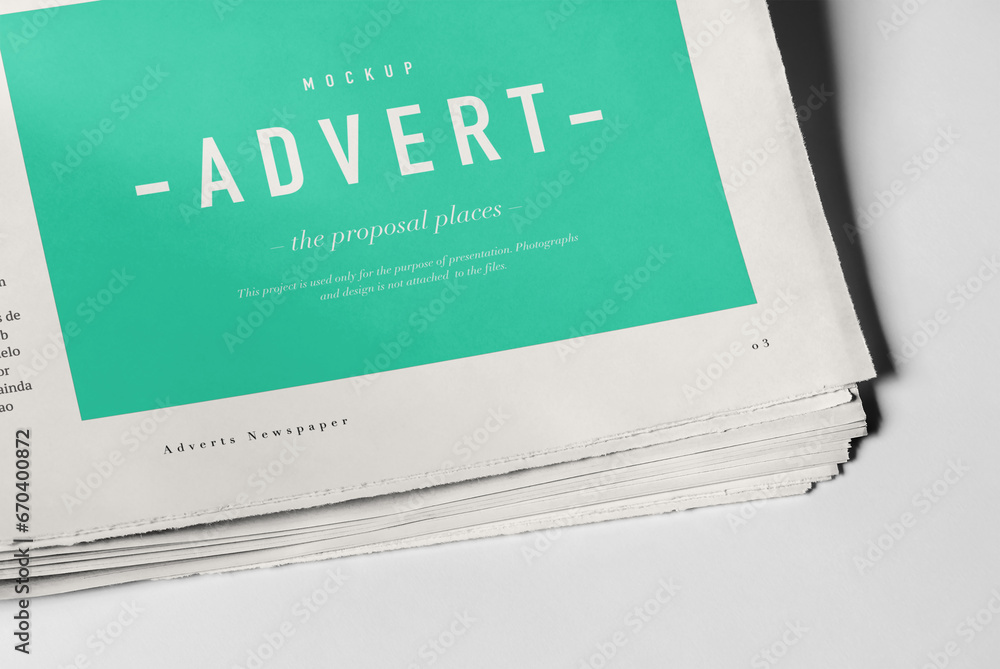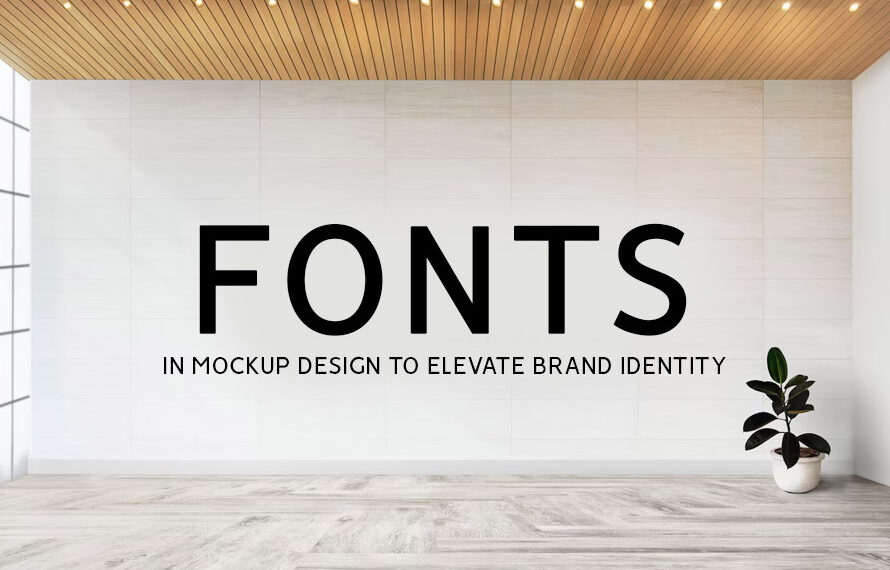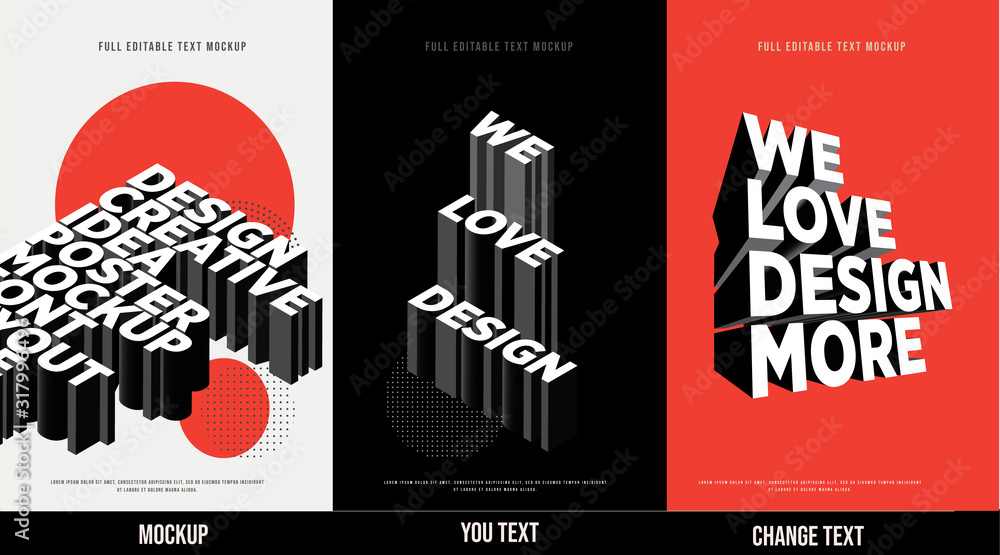
Fonts In Mockup Design
Nutzung von Schriftarten im Mockup-Design zur Steigerung der Markenidentität
Stellen Sie sich vor, Sie gehen eine belebte Straße entlang: Eine Flut von Geschäften zieht vorbei, die alle um Ihre Aufmerksamkeit konkurrieren. Plötzlich fällt Ihnen ein einzelnes Fenster ins Auge. Die klaren Linien, die fette Schriftart, die einladende Farbpalette – all das spricht Sie an und lädt Sie näher ein. Das ist die Kraft einer gut gestalteten Markenidentität.
Wenn es um Design geht, sind Ihre Schriftarten nicht nur Buchstaben auf einer Seite. Sie sind die Stimme Ihrer Marke, die Persönlichkeit und Zweck Ihrem Publikum zuflüstern. Tatsächlich können Ihre Schriftarten, einmal strategisch in Ihre Mockups integriert, wahre Magie entfalten, um Ihre Markenidentität zu verbessern. Lesen Sie weiter, um mehr zu erfahren.
Schriftarten in Ihrem Mockup-Design
Auswahl der richtigen Schriftart
Um Schriftarten in Ihrem Mockup-Design effektiv zu nutzen, ist Ihr erster Schritt die Auswahl der richtigen Schriftart. Denken Sie darüber nach, welches Gefühl Sie mit Ihrer Marke hervorrufen möchten. Verspielt und energiegeladen? Eine verspielte Skript-Schriftart könnte passen. Sophistiziert und zeitlos? Eine klassische Serifenschrift könnte die Antwort sein. Berücksichtigen Sie, wie die Schriftart mit der Kernbotschaft übereinstimmt, die Sie vermitteln möchten.
Fühlen Sie sich von all den Auswahlmöglichkeiten überwältigt? Keine Sorge, hier sind einige Faktoren, die Sie bei der Auswahl der idealen Schriftart beachten sollten.
Markenpersönlichkeit
Ist Ihre Marke verspielt und energiegeladen? Eine verspielte Skript-Schriftart könnte passen. Streben Sie nach einem anspruchsvollen und zeitlosen Eindruck? Eine klassische Serifenschrift könnte die Antwort sein.
Zielgruppe
Wen versuchen Sie zu erreichen? Ihre Schriftarten-Auswahl fällt leichter, wenn Sie die demografischen Merkmale und Vorlieben Ihrer Zielgruppe kennen. Zum Beispiel könnte eine jüngere Zielgruppe gut auf eine trendige, moderne Schriftart reagieren. Im Gegensatz dazu könnte eine professionelle Zielgruppe sich besser mit einer traditionellen Schriftart identifizieren.
Lesbarkeit
Die schönste Schriftart der Welt nützt Ihnen nichts, wenn sie schwer zu lesen ist. Priorisieren Sie Schriftarten mit klaren Buchstabenformen und angemessenem Abstand sowohl für digitale als auch für gedruckte Anwendungen.
Wählen Sie nicht einfach eine hübsche Schriftart aus! Die von Ihnen gewählte sollte eine strategische Entscheidung sein, die Ihr Design stärkt, Ihre Botschaft klar kommuniziert und bei Ihrer Zielgruppe Anklang findet.
Schaffen einer kohärenten Schrifthierarchie
Wenn Sie Ihre Markenidentität wirklich verbessern möchten, reicht eine einzige Schriftart möglicherweise nicht aus, egal wie gut gewählt. Mockups erfordern in der Regel eine Hierarchie von Schriftarten, von denen jede einen bestimmten Zweck erfüllt und die Kraft der Schriftpsychologie nutzt. Hier können Sie Ihr Designfeingefühl zeigen:
Überschriften
Fette, auffällige Schriftarten eignen sich ideal, um Aufmerksamkeit zu erregen. Wählen Sie Schriftarten, die Ihre primäre Schriftart ergänzen, aber genug herausstechen, um einen klaren visuellen Unterschied zu schaffen.
Fließtext
Hier befindet sich der Großteil Ihrer Nachricht. Wählen Sie eine Schriftart, die auf Bildschirmen und in gedruckter Form leicht zu lesen ist. Erwägen Sie den Einsatz einer serifenlosen Schriftart für ihre klaren Linien und Lesbarkeit, insbesondere für große Textblöcke.
Akzente
Verleihen Sie Ihren Elementen wie Handlungsaufforderungen oder Produktbezeichnungen mit Akzentschriften eine persönliche Note. Spielen Sie mit kontrastierenden Stilen, aber stellen Sie sicher, dass sie mit Ihrer Gesamtschriftartpalette harmonisch bleiben.
Scheuen Sie sich nicht, kreativ mit Ihrer Schrifthierarchie umzugehen. Mit einem durchdachten typografischen System können Sie Ihren Mockups eine zusätzliche persönliche Note verleihen. Dadurch können Sie Ihre gewöhnlichen Designs in außergewöhnliche verwandeln.
Schriftkraft in die Praxis umsetzen
Jetzt kommt der spannende Teil: die Anwendung Ihrer Schriftauswahlen auf Ihre Mockups. Hier sind einige praktische Tipps, um Ihre Markenidentität zu verbessern:
Konsistenz ist entscheidend
Konsistenz ist entscheidend für die Markenerkennung. Legen Sie einen Kernsatz von Schriftarten fest und halten Sie sich in allen Ihren Mockups daran, von der Websitegestaltung bis zu den Grafiken in den sozialen Medien. Dadurch entsteht eine kohärente visuelle Sprache, die die Menschen mit Ihrer Marke verbinden werden.
Farbkoordination
Schriftarten und Farben arbeiten Hand in Hand. Spielen Sie mit kontrastierenden Farben für Überschriften gegen einen
neutralen Hintergrund, um sie hervorzuheben und Aufmerksamkeit zu erregen. Möglicherweise möchten Sie auch ähnliche Farbtöne für Fließtext und Hintergrund verwenden, um ein Gefühl der visuellen Einheit und Ruhe zu schaffen.